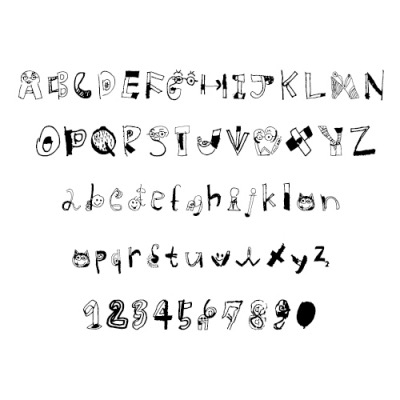
きゃらふぉんと
ArtistAyumi Kuroki
Designer福田 稜子
Organizationワークセンターひかわ
楽しいキャラクターのフォントです!自由な渋谷の街に合った個性的なキャラクターのフォントにしました。見出しや文章だけでなく,イニシャルで使ってもインパクト大!(福田 稜子)
一文字一文字相談しながら丁寧にデザインを決めて制作しました。制作者の普段描いている不思議なモチーフを,文字に活かしたいという発想から生まれたフォントです。(ワークセンターひかわ)